Как согласовать дуги в буквах «и», «ш» и «щ» рукописного шрифта
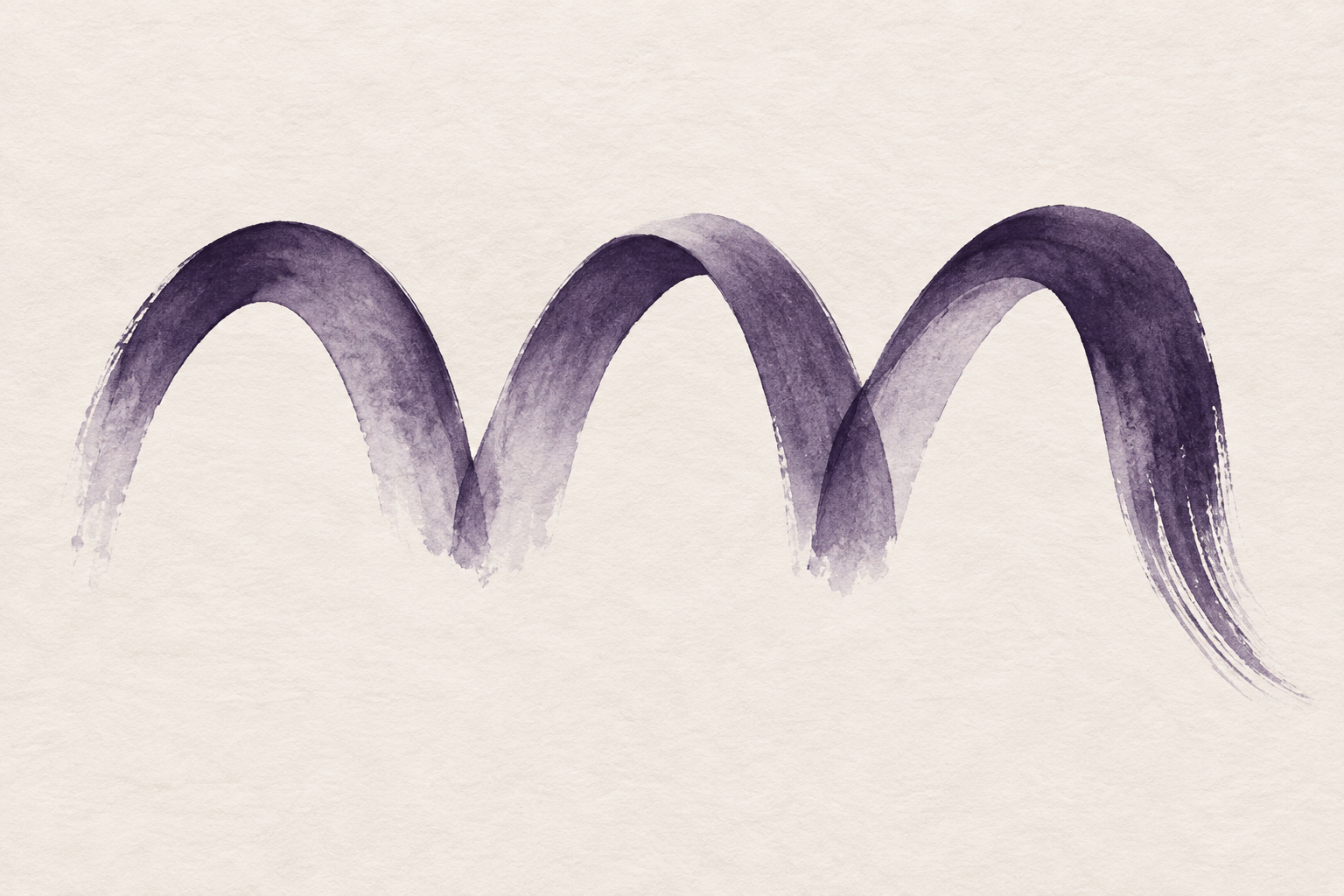
Дуги в строчных «и», «ш» и «щ» повторяют похожее движение, поэтому их удобно проектировать как небольшое семейство. Но буквам нельзя просто назначить одинаковые арки: у «и» один подъём и спуск, у «ш» несколько внутренних плеч, а у «щ» к конструкции добавляется выносной элемент. Сначала задайте общий характер дуги, затем настройте ширину, глубину и соединения каждой буквы по отдельности и проверьте их в словах.
Почему эти буквы стоит проектировать вместе
«И», «ш» и «щ» делят общую визуальную механику: нисходящий штрих соединяется с дугообразным переходом и снова поднимается или уходит в соединение. В печатном гротеске повторяемость может быть почти геометрической; в рукописной гарнитуре важнее сохранить естественный жест. Если каждая дуга нарисована без общей основы, буквы начинают выглядеть как знаки из разных почерков. Если все дуги скопированы один в один, слова превращаются в монотонную гребёнку.
Работа с семейством помогает найти середину между родством и различием. Вы выбираете общие признаки — радиус, характер входа в дугу, ширину штриха, степень округления вершины — и отмечаете, где контекст заставляет форму измениться. Такой подход экономит время: поправка базовой конструкции даёт отправную точку для нескольких букв. При этом он не подменяет оптическую проверку: итоговая форма каждой буквы должна читаться самостоятельно.
Сначала определите, какой именно жест вы рисуете
До настройки размеров решите, что означает «рукописный» в вашем проекте. Это может быть быстрый школьный почерк, спокойная каллиграфическая линия, округлая дружелюбная форма или более угловатый дисплейный рисунок. Дуга не существует отдельно от жеста: её характер задают скорость поворота, место смены направления, нажим и способ выхода в следующий штрих.
Нарисуйте несколько вариантов одного движения от руки, не пытаясь сразу сделать их аккуратными. Выберите не самую красивую отдельную арку, а ту, которую можно правдоподобно повторить в разных буквах. Для быстрой манеры поворот может быть коротким и упругим; для мягкой — более широким и плавным. Отметьте точку, где нисходящий штрих перестаёт идти прямо и начинает поворачивать, и участок, где дуга возвращается к следующему вертикальному движению. Это даст общий принцип, а не шаблон с фиксированными координатами.
Соберите основу на букве «и»
Начните с «и»: у неё достаточно простая конструкция, чтобы оценить один полный цикл вниз — через дугу — вверх. Задайте рабочую ширину, высоту строчной зоны и направление общего наклона. Затем сравните три свойства дуги:
- где начинается поворот относительно нижней точки буквы;
- насколько низко опускается соединительная часть;
- как быстро линия меняет направление на подъёме.
Не стремитесь к симметрии ради симметрии. В реальном движении вход и выход могут отличаться: рука подходит к дуге с одной скоростью, а покидает её иначе. Важно, чтобы различие выглядело намеренным и помогало переходу между штрихами. Если дуга похожа на острый угол, проверьте не только её радиус, но и то, не слишком ли поздно начинается поворот. Если буква кажется тяжёлой внизу, посмотрите, не задерживается ли там контур и не образует ли он заметную площадку.
После первого варианта поставьте рядом несколько «и» и попробуйте прочитать короткие слова. Одиночный знак часто кажется выразительным, а в серии обнаруживается повторяющийся провал, чрезмерная округлость или слишком резкий излом.
Перенесите принцип на «ш», а не контур
«Ш» удобно строить на основе ритма «и», но три дуги не должны выглядеть как механические копии одной петли. Внутренние переходы теснее связаны с соседними вертикалями: если верхушки арок слишком круглые, знак становится мягким и рыхлым; если слишком острые — возникает колючий, жёсткий ритм. Также меняется и общая ширина: три повторяющихся движения занимают больше места, чем один цикл.
Сначала определите число и положение штрихов, затем распределите промежутки между ними. Не сжимайте середину механически, чтобы вместить букву в заданный прямоугольник. Сравните «ш» с соседними строчными: будет ли она выглядеть тяжёлой, широкой или чрезмерно плотной в слове? В рукописном рисунке полезно отдельно проверить первую дугу, внутренние дуги и выходную сторону. Первая входит из предыдущего знака, средние участки создают повтор, а последний штрих готовит соединение дальше.
Если в «и» подъём закруглённый, это не значит, что все вершины «ш» обязаны иметь такую же форму. Можно сохранить общий характер перехода, но чуть уплотнить или раскрыть внутренние повороты, чтобы они не слипались визуально. Важно менять форму из-за функции участка, а не потому, что каждый элемент случайно нарисован по-разному.
Добавьте к «щ» отдельную логику выносного элемента
В «щ» основной ритм похож на «ш», но нижний выносной элемент сразу меняет силуэт. Если просто добавить хвост к готовой букве, он может казаться случайной приставкой: слишком длинной, тяжёлой или отделённой от общего жеста. Решите, откуда начинается нижний штрих, как он продолжает движение и насколько заметно выходит за основную ширину.
Проектируйте «и», «ш» и «щ» как родственные, но самостоятельные формы. Общая дуга задаёт алфавиту характер; роль участка, ширина и соединение определяют конкретное решение. Когда вы сравниваете отдельные буквы и короткие слова, повтор становится осмысленным ритмом, а не механическим копированием.